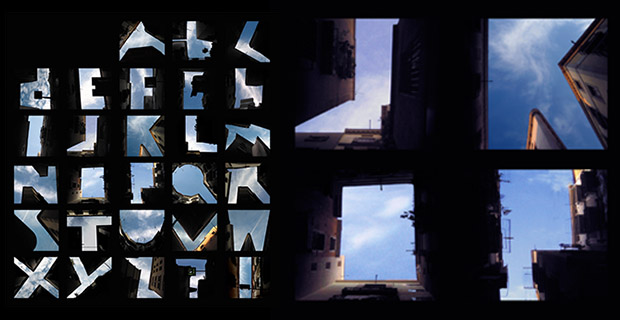
Tipografia in architettura: lettering, testi pubblicitari, strutturali e decorativi
Il matrimonio tra tipografia e architettura non è certo una recente invenzione e spesso ha dato vita ad insolite soluzioni progettuali. A lettere tondeggianti o squadrate, come semplici rivestimenti decorativi o supporti strutturali, i testi hanno conferito riconoscibilità e bellezza ad edifici in tutto il mondo, dal Fukutake House nell’isola Megijima in Giappone al Lentos Museum of Modern Art a Linz, in Austria. Visto a grande distanza o solo da molto vicino, il lettering è una dichiarazione inequivocabile del fabbricato e della sua destinazione.
In alto: Lisa Rienermann,Type the sky
Dall’architettura–pubblicitaria, vanitosa ed imponente, si passa ad eleganti organismi in cui sono i segni grafici ad aggiungere il valore evocativo e poetico. La tipografia diventa, a volte, solo sistema di riferimento e segnaletica fuori scala; altre volte, invece, questo lettering architettonico è visibile solo da alcuni punti e diventa strumento per affermare un concetto.
LA TIPOGRAFIA INVISIBILE E I PUNTI DI VISTA PRIVILEGIATI
I testi o lettere sono spesso percepibili solo da punti di osservazione privilegiati. Sono gli occhi dei passanti delle grandi città contemporanee o nei centri storici italiani, capaci di leggere forme e lettere nel cielo creati dalle cime degli edifici in ombra o dai muri dei cortili. Nella piccola Rotonda Foschini, nel teatro comunale di Ferrara, il visitatore guardando verso l’alto può ammirare un perfetto ovale, secondo una precisa volontà del progettista.
Nelle strade di Barcellona tra alti condomini e un cielo azzurro, la giovane artista Lisa Rienermann invece scopre un’inaspettata Q, la prima lettera del celebre alfabeto, chiamato Type the sky, che fotografa poi in altre città per completare la serie. I profili delle case e le piccole porzioni di cielo libere delineano, più o meno chiaramente, un nuovo font urbano. L’invito è all’osservazione e progettazione dei posti in cui viviamo più critica e fantasiosa.
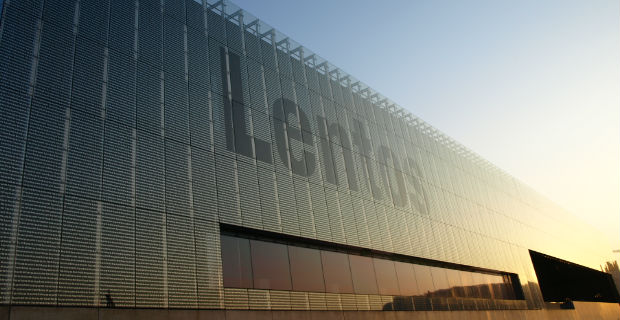
In alto: Lentos Museum of Modern Art, Linz
Altro punto di vista privilegiato del lettering è quello aereo, che dovrebbe essere molto più rivalutato data la grande diffusione di spostamenti in volo.
Le piante degli edifici, visibili dal progettista ma anche da vedute aeree, hanno da sempre imitato modelli naturali, animali e anche caratteri tipografici. È il caso dell’alfabeto di Steingruber, pubblicato nel 1773,doveogni lettera dell’alfabeto costituisce la pianta di un’architettura. L’intero alfabeto, con due varianti per la lettera A, è però rimasto solo sulla carta.
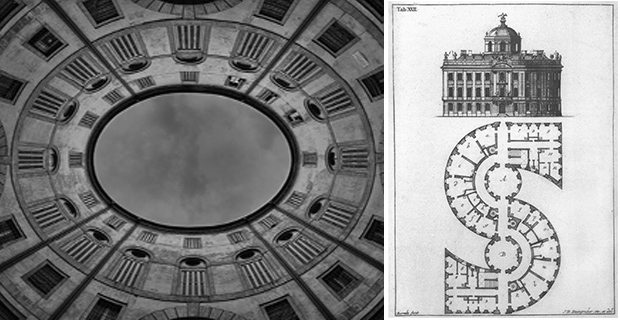
In alto: a sinistra, Rotonda Foschini (Ferrara); a destra, Alfabeto di Steingruber, 1773
Alcuni progettisti usano la tipografia a caratteri cubitali.
Per esempio nel Wales Millennium Center a Cardiff, la facciata in ardesia presenta un testo intagliato e chiuso da vetri, che recita in gallese ed inglese “In These Stones Horizons Sing – Creu Gwir Fel Gwydr O Ffwrnais Awen”. Questo a ricordare che anche le pietre dell’edificio letteralmente cantano assieme all’opera, ai musical e all’orchestra presente all’interno.
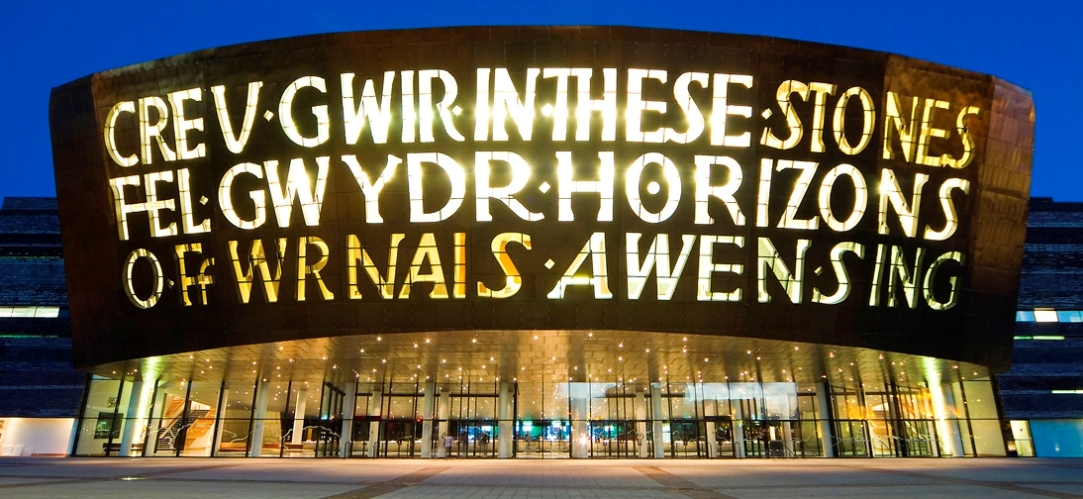
In alto: Wales Millennium Center, Cardiff
Nel sopracitato Fukutake House del 2010, installazione annuale per promuovere l’arte nelle comunità rurali, un gigantesco testodorato dal font sans serif ricopre le facciate della scuola elementare che ne ospitava l’edizione.
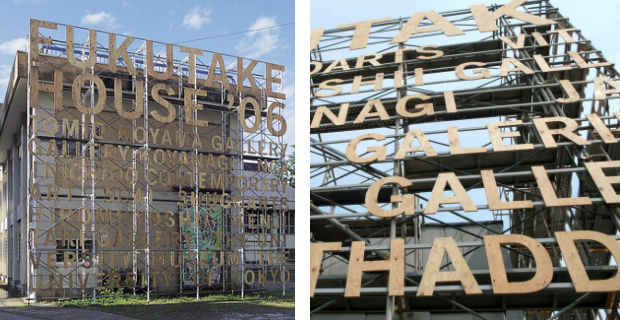
In alto: Fukutake House
Quasi agli antipodi i testi del Lentos Museum of Modern Art daldesign tipografico leggerissimo ripetuto e distinguibile solo da vicino, e l’House of Terror, a Budapest in Ungheria dove il testo “Terror” in grassetto ha davvero un impatto sensazionalistico e urlato. Quando il sole batte sul tetto dell’edificio, le lettere ritagliate riportano la scritta sulla facciata e gridano la violenza perpetuata nell’interno prima dalla polizia nazista e, poi, da quella comunista.
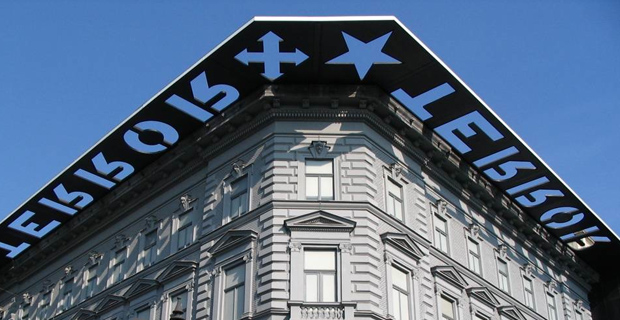
In alto: House of Terror, Budapest
Ultimo esempio è a New York, il Cooper Union, dove Abbott Miller studia una segnaletica completamente integrata all’edificio dei Morphosis, spigolosa e futuristica. A cominciare dalla facciata, il nome dell’edificio è scritto con il font Foundry Gridnik estruso, che ricorda quello usato nell’edificio storico.
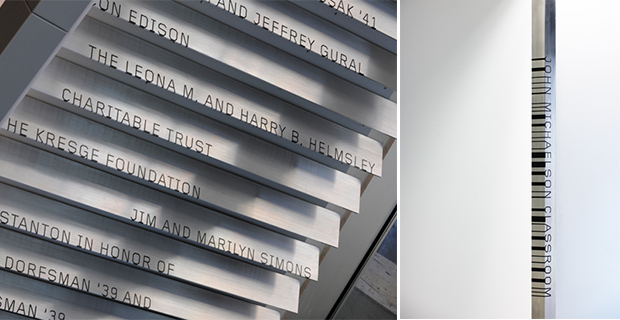
In alto: Cooper Union, New York, Morphosis Architects
La tipografia si concretizza in diversi ed inaspettati modi: scende giù dall’intradosso delle scale, si adegua ai paraspigoli delle porte delle aule e appare come una costellazione di nomi incisi nel granito.